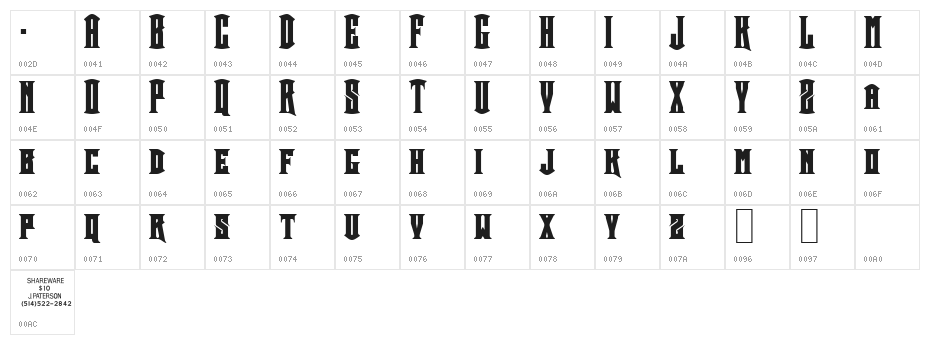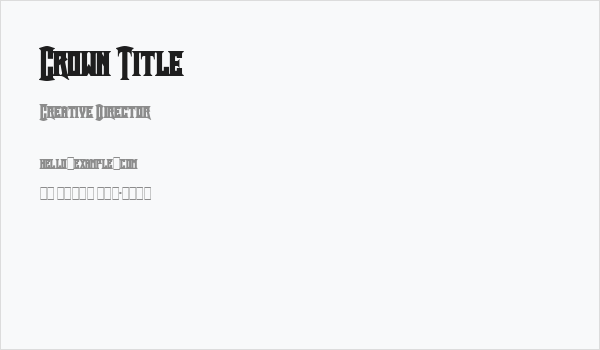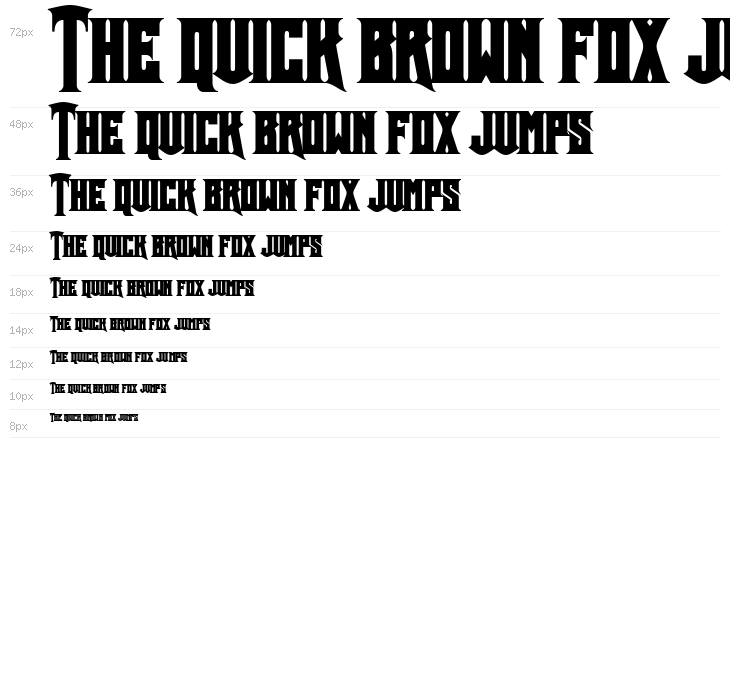
Crown Title Font
Fonts by Jonathan Paterson
| Progetti proposti | Ideal for projects that require a strong visual impact, such as posters, album covers, or branding for edgy or alternative products. |